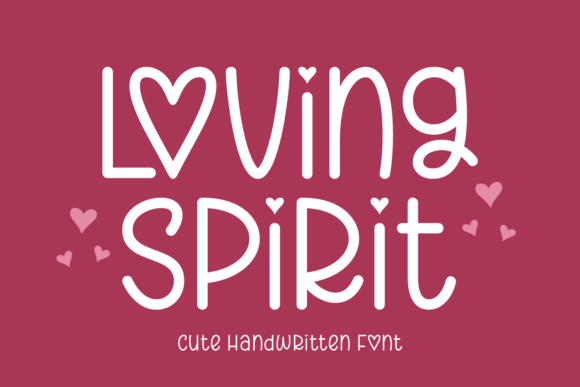
Loving Spirit
Пошук відповідних елементів дизайну може бути складним, але Loving Spirit пропонує виняткову колекцію, яка миттєво покращить вашу роботу.
Створений з високою точністю, Loving Spirit забезпечує чисті вектори, плавну типографіку та комерційну ліцензію для вашого спокою.
Незалежно від того, чи створюєте ви продукти POD (друк на вимогу), весільні запрошення або графіку для соціальних мереж, Loving Spirit стане ідеальним вибором.